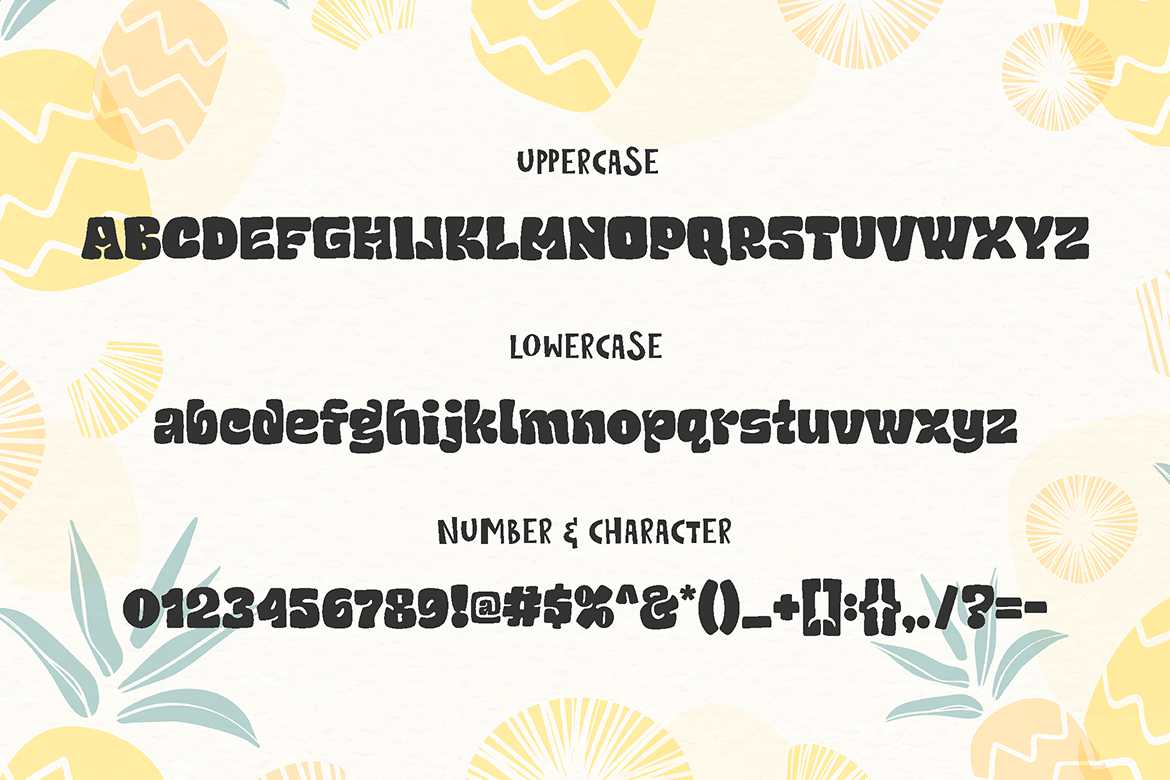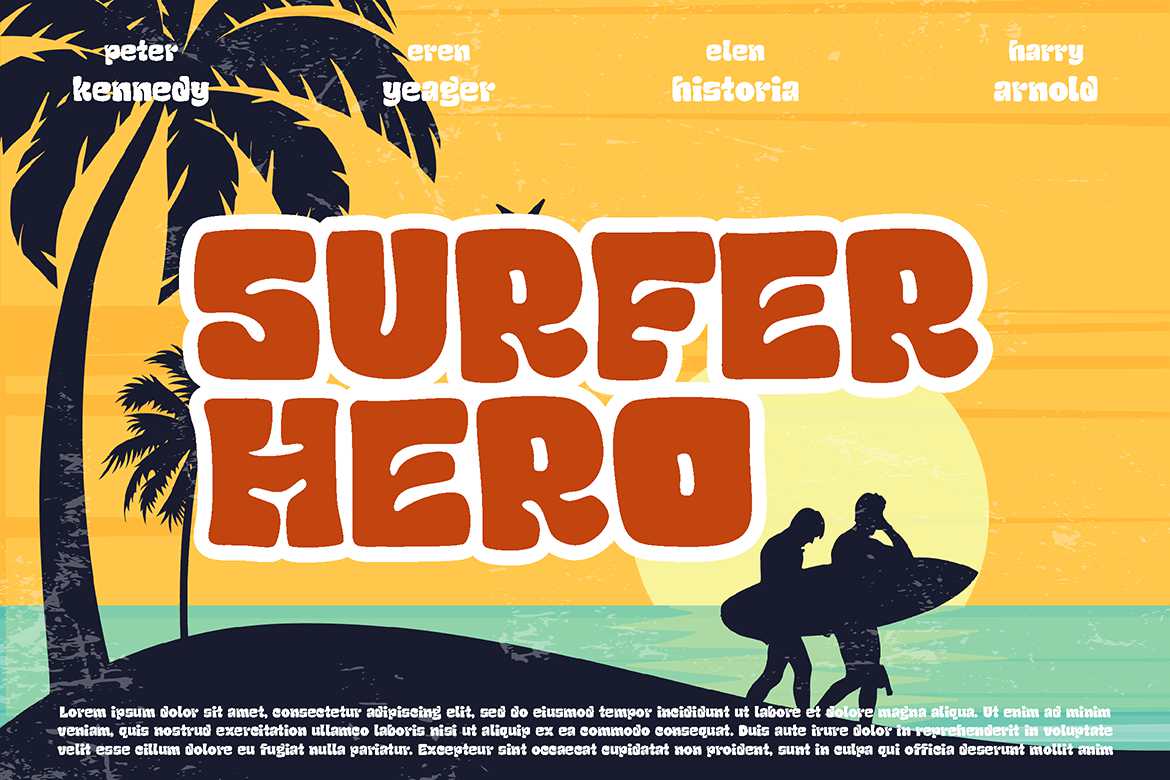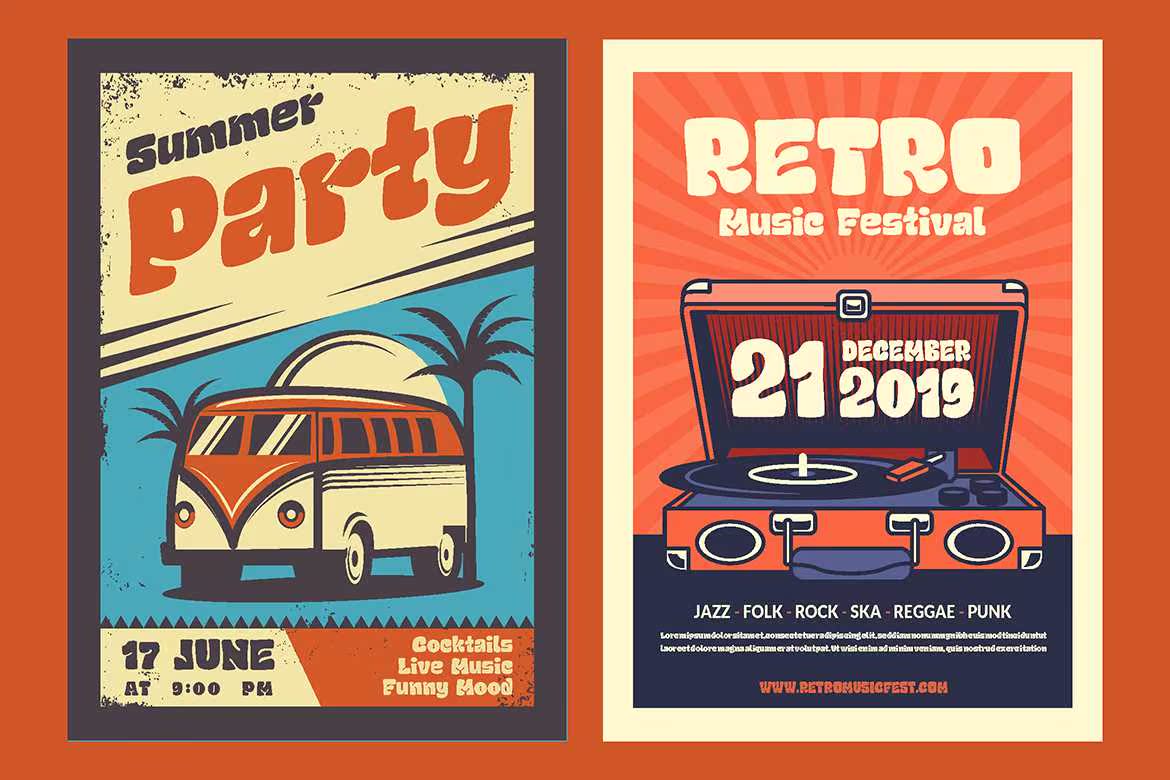
“谁说的是适合老年人的?”胖乎乎的Roovy打破了界限。它以前所未有的方式给老年人带来快乐和童趣。非常适合于复述海报、复述和娱乐节目、电影、海滩酒店菜单、杂志、青年读者、青少年指甲、,《社交媒体封面》和《很快》…谁说这只适合老年人?胖乎乎的书突破了界限。它以前所未有的方式带来了快乐和儿童的态度。非常适合于《追忆海报》、《追忆与追忆》杂志、电影、海滩酒店菜单、杂志、青少年杂志、青少年杂志、社交媒体封面和《很快》…